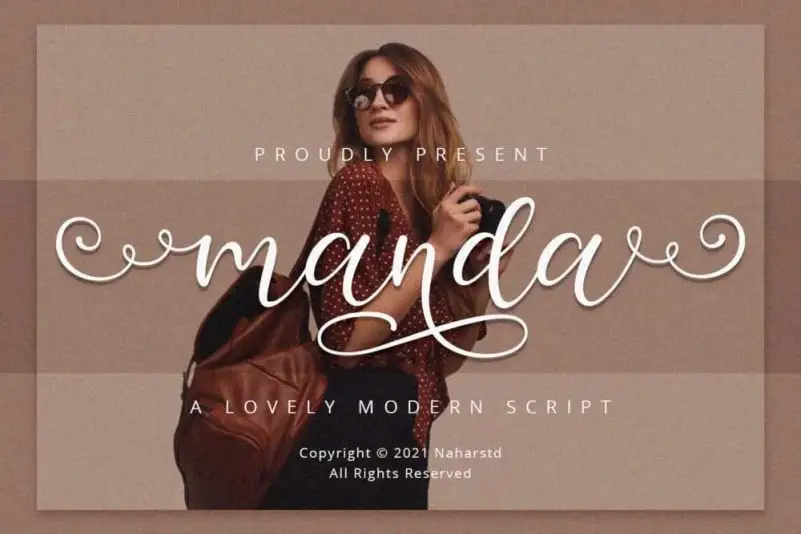
Manda Calligraphy Font – Download Grátis
A Manda Calligraphy Font é uma elegante fonte de script manuscrito criada por Naharstd, com base em traçados manuais que dançam sobre uma linha do fundo e contêm muitos alternativos e ligaturas. Através da sua personalidade irresistível, a Manda Calligraphy é perfeita para um amplo espectro de criações gráficas como convites de casamento, cartões de agradecimento, citações, cartas de boas-vindas, logotipos, cards de negócio, marcação, design de mobiliário, embalagens de produtos, t-shirts, capas de livros, cartões de convite, cartas de boas-vindas, etiquetas, fotografias, marcas e eventos especiais. Com a Manda Calligraphy Font em seu arsenal de ferramentas, qualquer designer gráfico pode transformar qualquer design em algo que pareça ser escrito à mão. Ela é uma ótima escolha para aqueles buscando uma fonte única e personalizada para suas criações específicas.